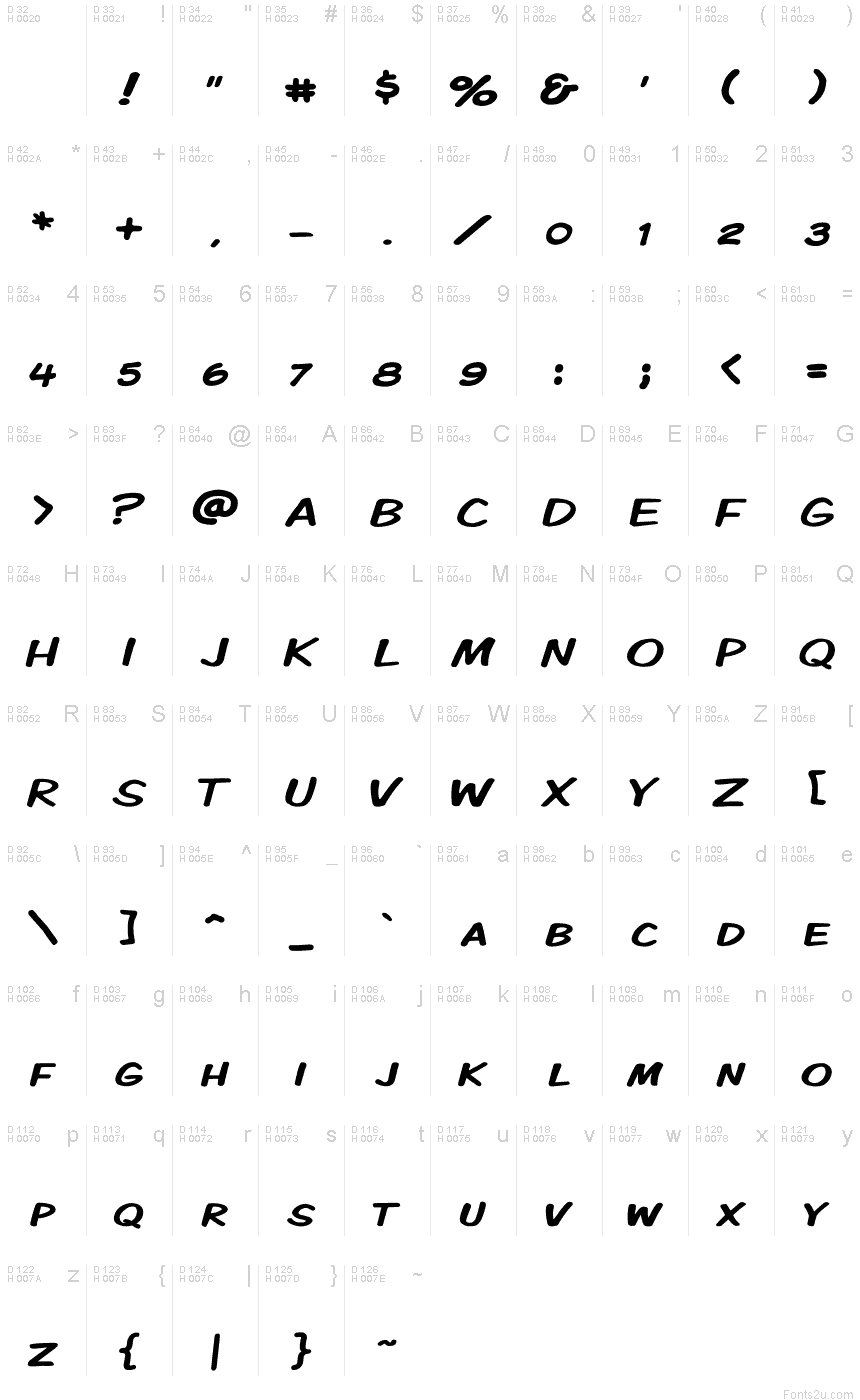
Komika Display Kaps Wide od Wolfbainx & Apostrophic Labs to darmowy krój typu comic display. Masywne, wielkie litery sprawiają wrażenie ręcznie malowanych, z lekkimi, urokliwymi niedoskonałościami i szerokimi liniami, które pozostają czytelne nawet przy dużej ilości kolorów i efektów. Szeroka postawa i miękkie krzywizny nadają mu wyrazisty, ale przyjazny charakter, idealny do przyciągających uwagę nagłówków, bez efektu sztywności czy sztampy.
Używając Komika Display Kaps Wide, nadasz energii okładkom komiksów, plakatom na imprezy dla dzieci, tytułom gier, miniaturkom na YouTube, naklejkom czy odważnym grafikom do social mediów. Ten darmowy font sprawdza się świetnie w dużych rozmiarach, gdzie jego grube, „tuszowe” kształty naprawdę robią wrażenie. W przypadku tekstu towarzyszącego, zestaw go z lekkim, geometrycznym bezszeryfowym krojem, aby uwaga skupiała się na tych energicznych wielkich literach.
Komika Display Kaps Wide